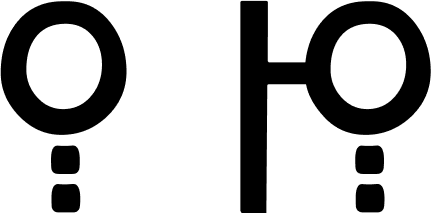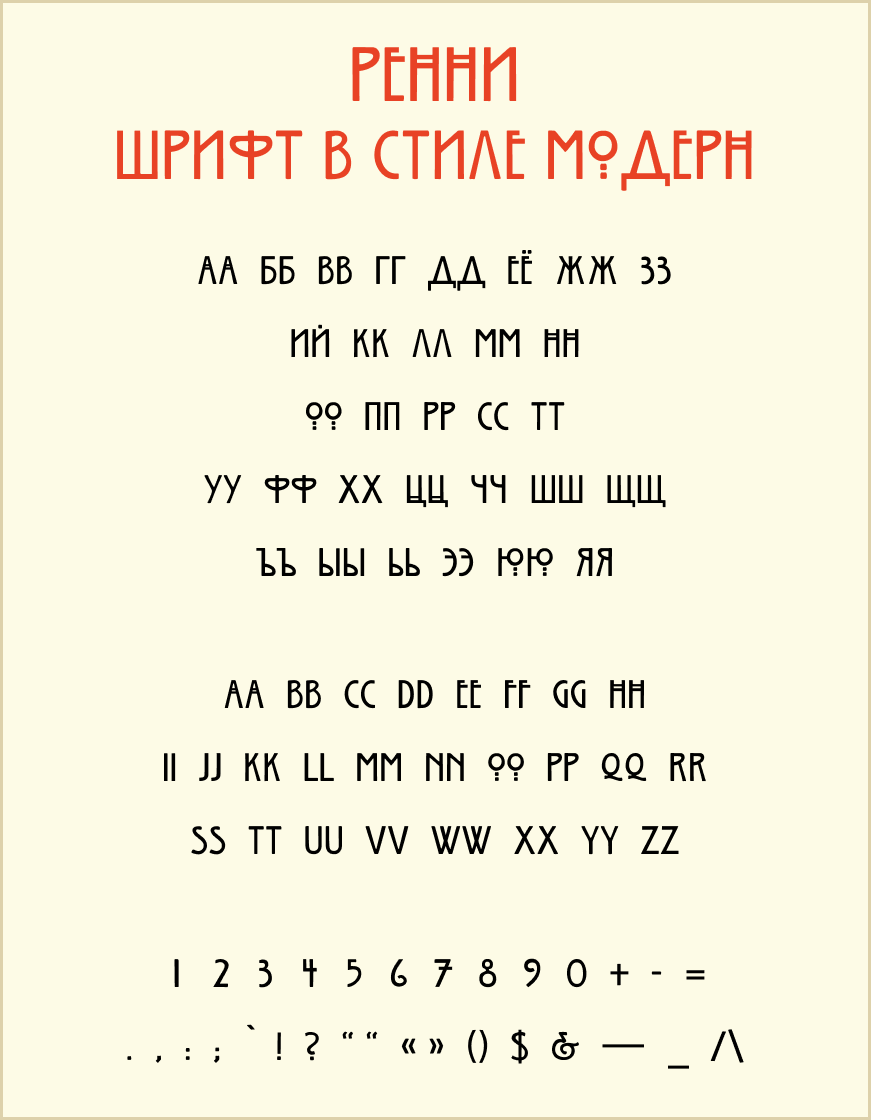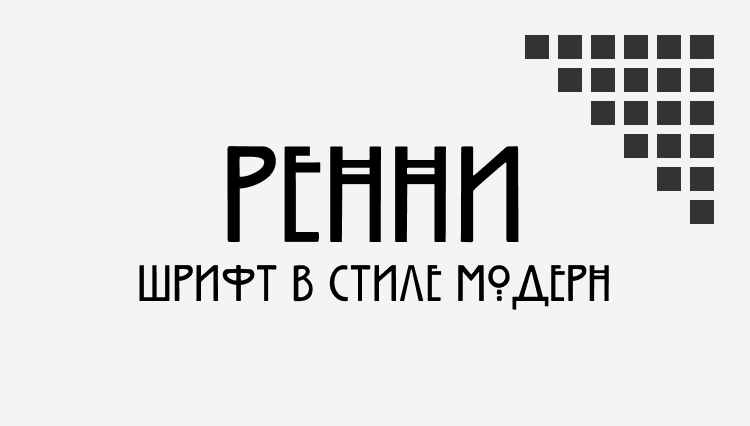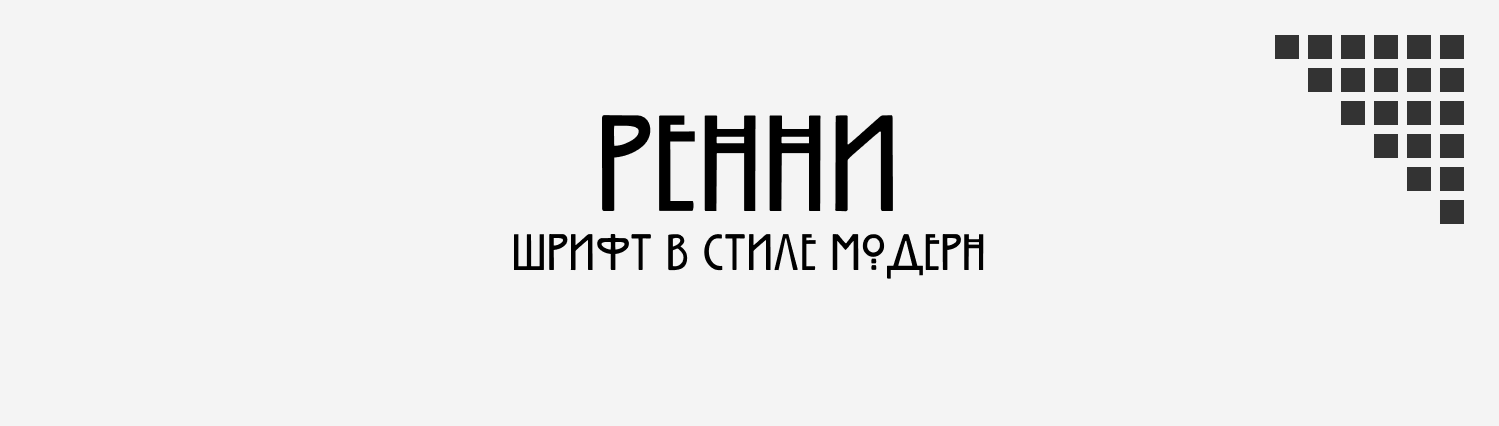
Шрифт в стиле модерн Ренни
Шрифт Ренни посвящен Чарльзу Ренни Макинтошу. Ренни — это кириллическая версия шрифта ITC Willow. Шрифт выполнен в стиле модерн и является отсылкой к надписям на Школе искусств имени Макинтоша в городе Глазго.
Шрифт Ренни хорошо подойдет для стилизованных под модерн начала 20-го века надписей. Буквы «А» и «Н» имеют свойственную модерну двойную перекладину.
Буква «О» выполнена оригинальным способом. Сама буква маленькая и сдвинутая вверх, форму поддерживают две точки. Аналогичная форма у русской буквы «Ю».
Используйте шрифт Ренни для набора надписей и вывесок в дореволюционном стиле и стиле модерн.
Чарльз Ренни Макинтош
Чарльз Ренни Макинтош — шотландский архитектор, художник и дизайнер, родоначальник стиля модерн в Шотландии. Макинтош разработал особый декоративный стиль, в котором геометрические элементы связываются качающимися, разлетающимися по сторонам линиями, который на рубеже XIX—XX столетий был типичен для европейского декоративного искусства.
В своих архитектурных и дизайнерских проектах использовал метод «изнутри наружу» — и дом, и мебель, и внутренняя отделка проектировались как единая гармоничная система. Вещи Макинтоша всегда геометричны и функциональны, имеют стройные пропорции и не обременены излишним декором.
Чарльз Ренни Макинтош стал новатором конструктивной линии модерна с характерной для неё прямолинейностью форм и их ясным построением. Его мастерство было основано на типично столярной геометрически прямолинейной конструкции с преобладанием вертикальных линий.